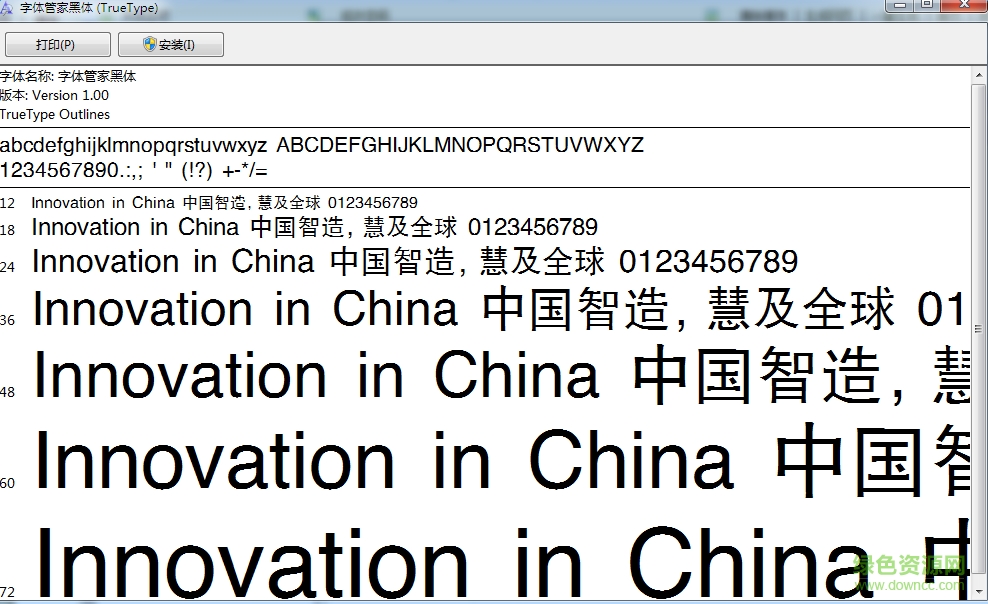
字體管家黑體
字體管家黑體字體是一款字面呈正方形的粗壯字體,字形端莊,筆畫(huà)橫平豎直,筆跡全部一樣粗細(xì),結(jié)構(gòu)醒目嚴(yán)密,非常適用于標(biāo)題或需要引起注意的醒目按語(yǔ)或批注,喜歡可以來(lái)綠色資源網(wǎng)下載!
字體簡(jiǎn)介
字體管家黑體是一款用于裝飾的字體,吸收了宋體字結(jié)構(gòu)嚴(yán)謹(jǐn)?shù)膬?yōu)點(diǎn),在筆畫(huà)的形狀上把橫畫(huà)加粗且把宋體字的聳肩角削平為等線狀,形成橫豎筆畫(huà)粗細(xì)一致,變宋體字的尖頭細(xì)尾和頭尾粗細(xì)不一的筆畫(huà)為方形筆畫(huà)!